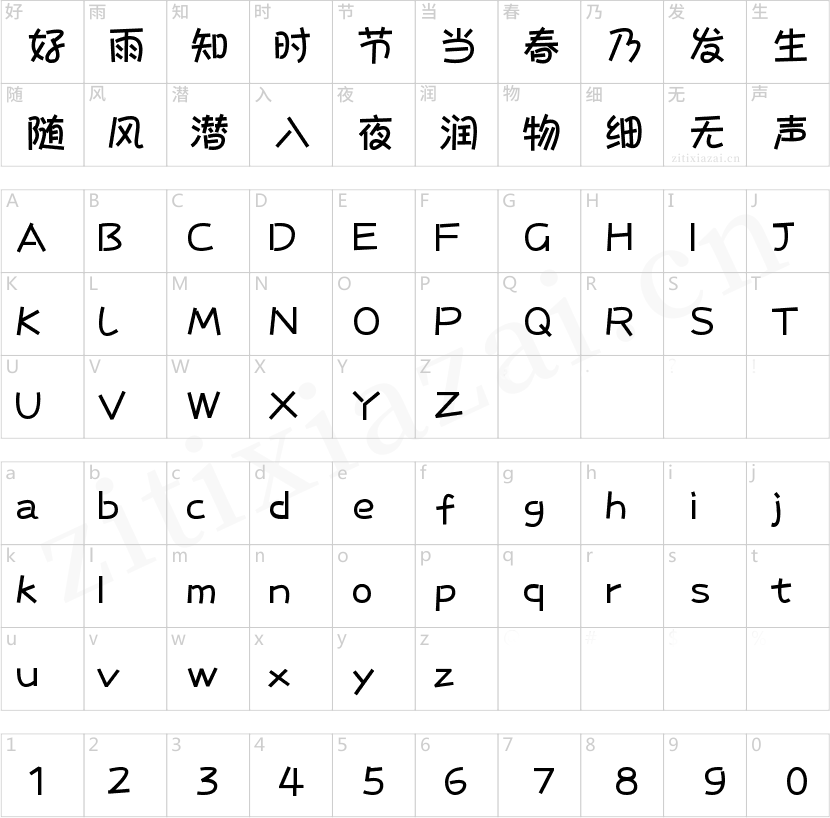
壹心高兴体
壹心高兴体,这款字体结构工整、笔画清晰,兼顾美观与易读性,适用于标题、正文、海报、包装、LOGO 等多种场景。字形优雅稳定,风格百搭耐看,适配日常排版与创意设计,让文字呈现更舒适、更具质感。壹心高兴体一笔一画,皆是细节,以均衡的比例、流畅的线条打造舒适视觉体验,字形端正大气,风格简约现代。无论是商业设计、品牌宣传还是日常排版,都能轻松驾驭,让文字更有格调与力量。壹心高兴体字体下载。